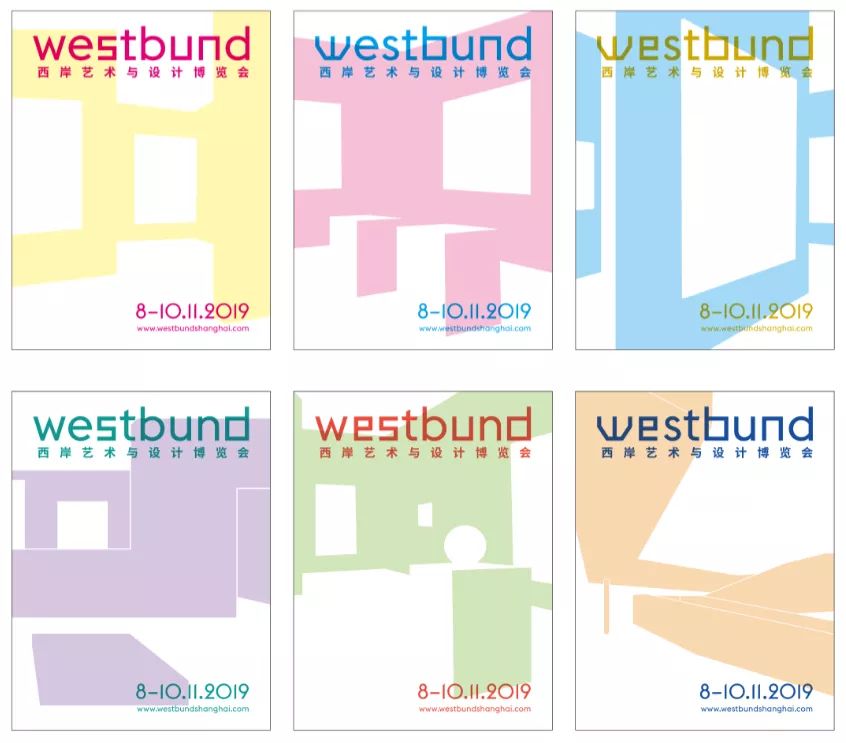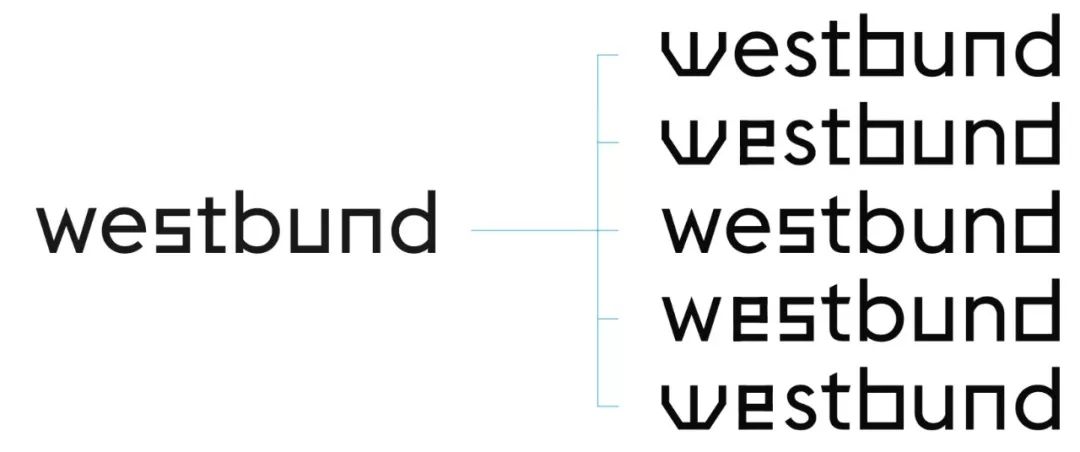
2019西岸艺术与设计博览会,发布全新视觉识别系统!
西岸艺术与设计博览会官方宣布启用全新视觉识别系统。这是博览会自2014年创建以来,品牌形象从形态到理念做的一次彻底地更新换代。
2019年西岸博览会logo(英)
2019年西岸博览会logo(中英)
全新视觉识别系统由享誉全球的荷兰著名设计工作室thonik设计。在其接受该项任务之后,对西岸博览会进行了较长时间的品牌调研。
thonik 分析“West Bund”的各种阅读和书写方式,最终决定采用 Euclid Flex 小写字体合并版本:westbund。小写字母具有流动性和镜像特质,整体则显得独特而简洁,既指明了博览会所处的地理位置,也与“西岸”片区的视觉图标有所区分,同时具备了几何结构和俏皮细节。
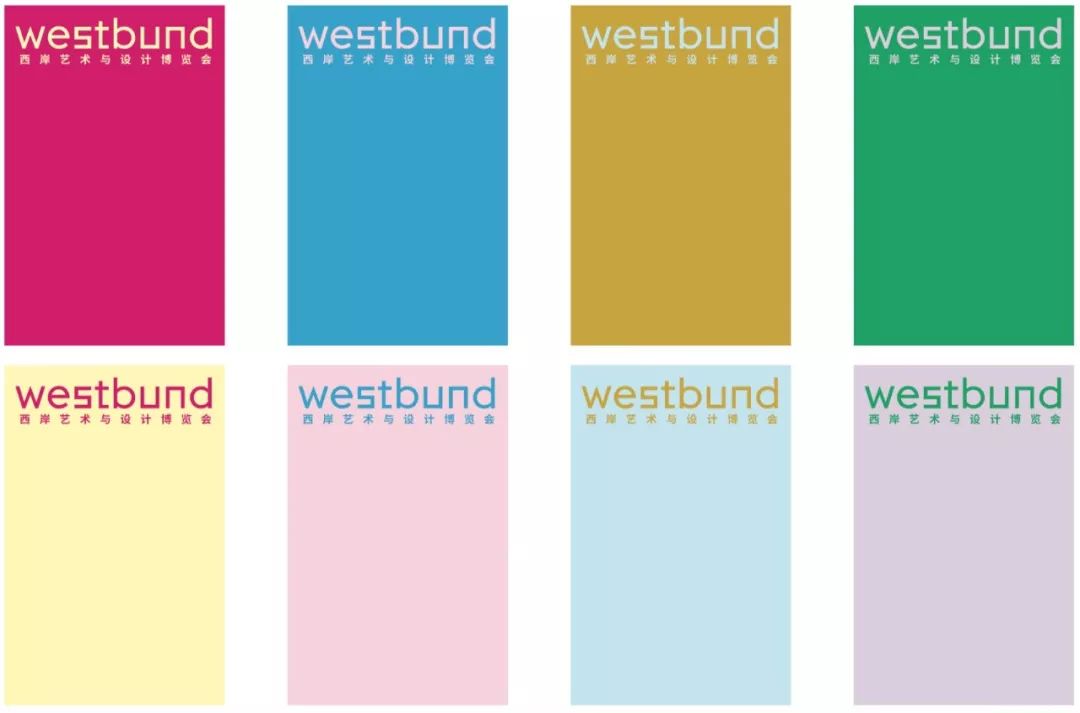
thonik 专注于视觉传达设计,尤其是视觉身份、互动设计和动态设计,他们喜欢将设计和媒介大胆探索结合起来。遵循这一理念,thonik 尝试混合和互换字母,最终产生由动态的字母形式发展而成的博览会崭新形象。
如今,互联网新媒体时代,人们与logo和视觉图标的互动主要发生在数字与电子屏幕上,新的 westbund 视觉识别系统保持了现代特征,并支持及时与持续地变化去融入数字化世界。有别于传统固定静止的视觉应用,新视觉识别系统可以通过字体形状的变化呈现出多样的动态感,从一个延伸出“无穷”个同一名义的新形象,并可自由选择在不同语境下的运用;整个视觉印象从原有的固定即视感更换成具有超前意识的可变多维性,引领当下艺术与设计的时代精神。